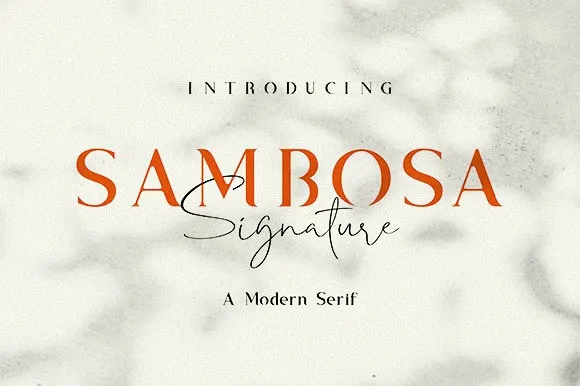
Sambosa Font – Fonte Grátis
Sambosa Font
Sambosa Font é uma elegante tipografia serifada que incorpora elementos modernos com um toque de charme art déco, criando um clássico moderno perfeito para logos, panfletos, convites de casamento, posts do blog e mídias sociais. Suas linhas arredondadas e detalhes delicados garantem um tom sofisticado que traz vida a qualquer projeto visual. Seja para uma identidade empresarial profissional ou uma peça de arte gráfica atemporal, Sambosa Font é o selo perfeito. Este design da 99designs oferece uma mistura única e inspiradora, ideal tanto para aqueles que buscam um toque clássico quanto para quem valoriza a inovação contemporânea.